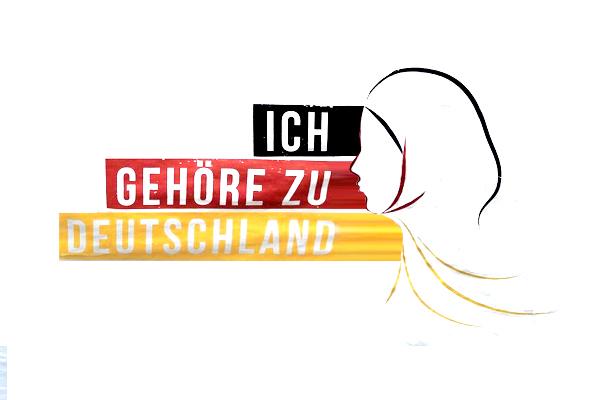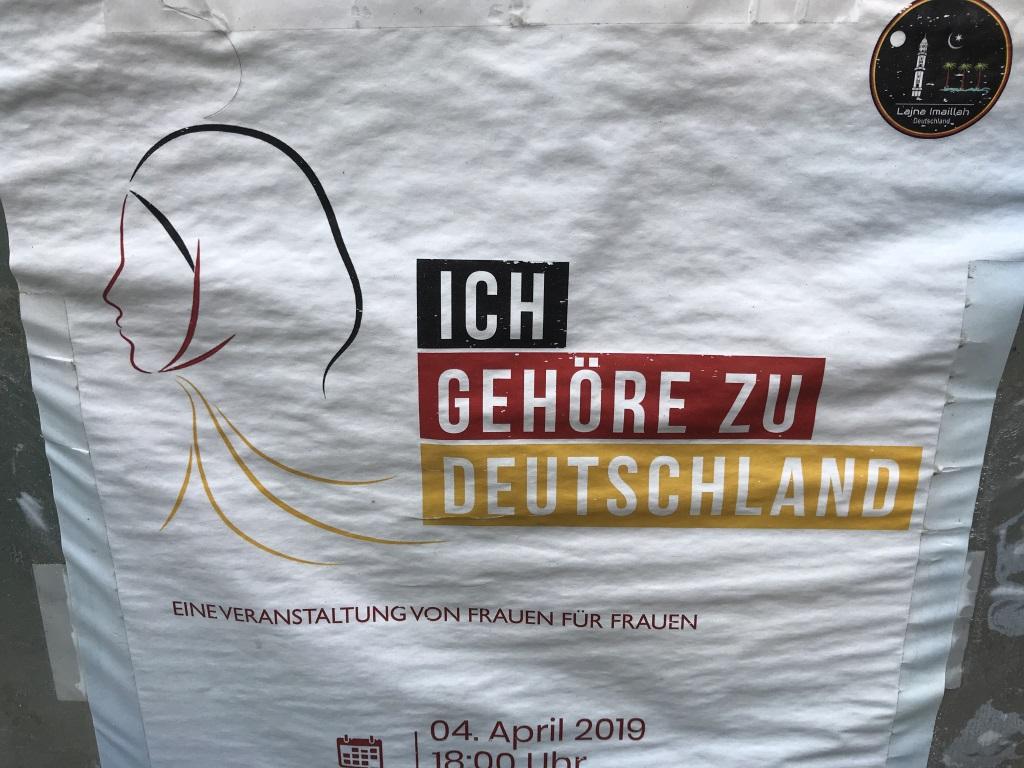
Ich find das Logo extrem sprechend und schön.
Und bitte keine inhaltlichen Diskussionen!
In Ordnung! Also: Ich finde den Gestaltungsansatz auch ansprechend, aber formal ist mir der Kontrast zwischen der Zartheit der Zeichnung und dem mit fetten Balken unterlegten Schriftzug zu krass. Und ich frage mich, warum sich die Frau von der Textaussage abwendet, das widerspricht sich doch? Da könnte man fast schon von Bild-Text-Schere sprechen. Und die Führungsnull im Datum dürfte auch gerne weg, das ist aber eine Marginalie. Mein Fazit zu diesem Motiv: Guter Ansatz, aber noch ein bisschen ausbaufähig. :-D
Kontrast zwischen der Zartheit der Zeichnung und dem mit fetten Balken unterlegten Schriftzug
warum sich die Frau von der Textaussage abwendet
Ach, danke, da kann ich mir meine eigene Tipperei komplett sparen! :gimmifive:
Der Kopf für sich ist allerdings sehr schön. Den könnte ich mir – in dieser Farbgebung¹ – auch ganz ohne Text auf T-Shirts, Aufklebern, Tassen etc. vorstellen. Die Botschaft sollte doch rüber kommen, oder?
ps     1. Na gut, das Rot vielleicht eine Spur heller. So wie in der 🇩‍🇪 eben.
pps   Ach, und eine ganze Serie solcher Zeichnungen könnte ich mir auch vorstellen. Ein Kopf mit Kippa, zwei einander küssende Männer- oder  Frauenköpfe, ein Wolfs(kopf) …
Und ich frage mich, warum sich die Frau von der Textaussage abwendet, das widerspricht sich doch?
Vielleicht ist das bei der Zielgruppe kein Widerspruch, da sie eine andere Leserichtung gewohnt ist? Der Kiosk, der das auf einem Aufsteller (Wie hießen die noch? Irgendwas mit Stopper) plakatierte, hat sonst dort mehrheitlich Plakate mit mehr arabischer als lateinischer Schrift (ich glaub, nur der Ort ist auf Deutsch). Ich werde die Ecke aber mal beobachten, ich mag ja so Multikulti und so... Und wenn die dort beworbene Moschee mal eine Veranstaltung anbietet, die mich interessiert, geh ich auch mal hin.
Aber wäre auch dann Christians Version nicht besser: erst das Subjekt, dann ihre Aussage (die ihr geradezu aus dem Mund sprudelt)? Im Original hingegen knallt der Spruch ihr an den Hinterkopf.
Bei Leserichtung von rechts wäre die Treppe in der modifizierten Version natürlich absteigend. Ich fand es gut, dass sich durch die Schieberei (bei Leserichtung von links) zufällig eine aufsteigende, positive Treppenform ergab. Wenn man in den Kopf noch spiegeln und nach links verschieben würde, wäre die mMn schöne Anordnung von Figur und Grund wieder im Eimer, andererseits würde sie dann in die Zukunft schauen“ und vielleicht könnte die Treppe als Sprechblase umfunktioniert werden? Eventuell ergäbe sich dabei aber auch eine klaffende Lücke zwischen Figur und Aussage, wenn der Text weiterhin rechtsbündig angeordnet wird...
Die Aussage am Hinterkopf empfand ich auch als störend, aber ich kann gut nachvollziehen, warum es so gemacht wurde.
Etwas Hintergrund:
Ich hab mir mal das Logo oben weiter vergrößert, um den Veranstalter zu identifizieren, es ist die Frauenorganisation der Ahmadiyya Muslim Jamaat, die auch eine eigene Website betreibt, mit einem anderen Logo, dass ich in seiner Anmutung auch wieder sehr gelungen finde: http://www.stimmedermuslima.de
Und ich habe damit heute eine neue muslimische Richtung kennengelernt. Irgendwie spannend, wie sehr die Nachrichten von Schiiten und Sunniten dominiert werden, ab und wann ein paar Derwische und Drusen dazwischen blitzen... Da jene Richtung aus Indien stammt, kann ich mir vorstellen, dass die in Großbritannien deutlich verbreiteter sind.
Was übrigens die Bildsprache wieder ein Tick komplizierter werden lässt, weil die Zielgruppe gleich dreieinhalb Kulturen entspringt (türkisch, arabisch, indisch und (ein bißchen) deutsch).
Am ‎04‎.‎05‎.‎2019 um 11:26 schrieb Phoibos:
Etwas Hintergrund:
Ich hab mir mal das Logo oben weiter vergrößert, um den Veranstalter zu identifizieren, es ist die Frauenorganisation der Ahmadiyya Muslim Jamaat, die auch eine eigene Website betreibt, mit einem anderen Logo, dass ich in seiner Anmutung auch wieder sehr gelungen finde: http://www.stimmedermuslima.de
Jetzt hast du es letztendlich total aus dem Zusammenhang gerissen und dem Satz eine Gemeingültigkeit unterstellt, die nie beabsichtigt war 8-) Diesen kantschen Anspruch würde ich auch nie niemals nicht stellen. Aber ich rede mit meiner Frau anders als mit meiner Mutter oder meinen Kindern – das heißt aber nicht, dass die nicht auch untereinander kommunizieren könnten. Wenn ich alle drei gleichermaßen mit gleichem Effekt Ansprechen  will, wird es kompliziert …